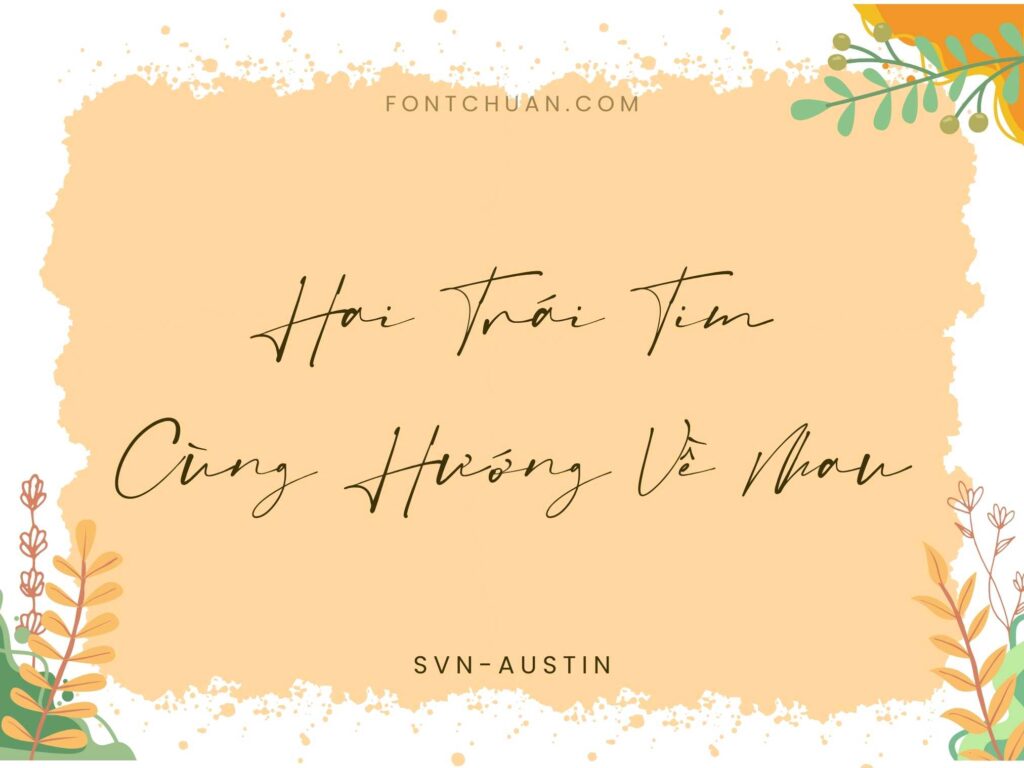
Font SVN Austin Việt Hóa
Tác giả Font: Vultype Co
Font SVN Austin là phiên bản Việt hóa của kiểu chữ Austin, được thực hiện bởi Styleno.1 Fonts. Austin là một kiểu chữ viết tay hiện đại, nổi bật với các đường nét mềm mại và tự nhiên, tạo cảm giác thân thiện và gần gũi. Font này thích hợp cho nhiều mục đích sử dụng khác nhau, từ thiết kế thiệp mời, logo đến các ấn phẩm truyền thông.
SVN Austin lý tưởng cho các dự án thiết kế yêu cầu sự cá nhân hóa và sáng tạo, như thiệp mời, logo và các ấn phẩm truyền thông. Các ngành nghề như thiệp cưới, ẩm thực và spa có thể tận dụng font này để tạo điểm nhấn trong thiết kế. Ngoài ra, font cũng thích hợp cho các sự kiện như Tết, Valentine, Sinh nhật và các lễ hội khác.